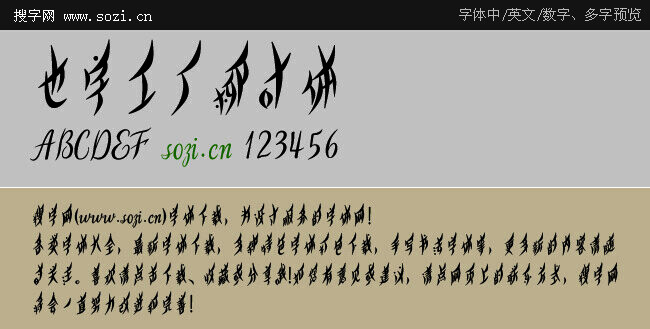
也字工廠柳葉體
搜字網(wǎng)給大家提供一款也字工廠柳葉體中文藝術(shù)字體下載,也字工廠柳葉體字體傾斜修長(zhǎng),娟秀清瘦,宛如柳葉,又似月亮,在保持識(shí)別性的前提下 簡(jiǎn)化豎提、橫折鉤、豎彎鉤等的設(shè)計(jì)使字體整體更具統(tǒng)一性,在同一個(gè)字體中,筆畫粗細(xì)差別較大,更有手寫的輕松感和人文感。適合應(yīng)用于海報(bào)設(shè)計(jì)、包裝設(shè)計(jì)、網(wǎng)頁設(shè)計(jì)等應(yīng)用。